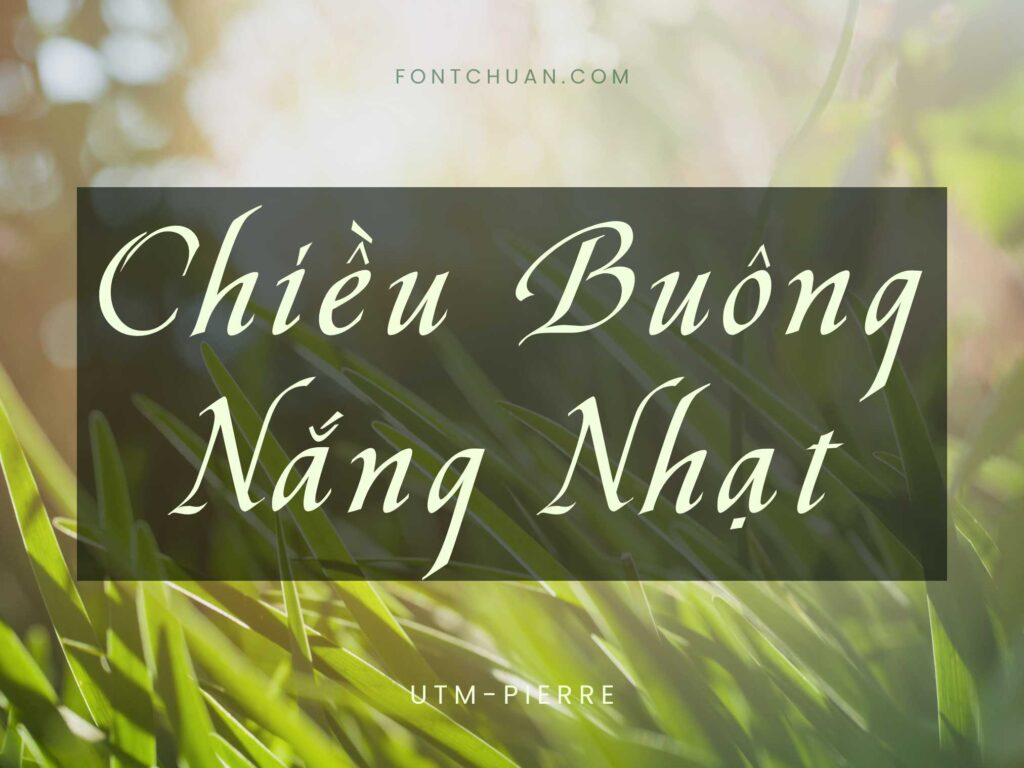
Font UTM Pierre Việt Hóa
UTM Pierre là một font chữ serif mang phong cách cổ điển và sang trọng, được thiết kế để tạo nên sự tinh tế và chuyên nghiệp trong các dự án thiết kế đồ họa. Font này có các đường nét thanh mảnh, độ tương phản cao và chân chữ rõ ràng, giúp tăng cường khả năng đọc và thu hút sự chú ý. Font đã được Việt hóa để hỗ trợ tiếng Việt, mở rộng khả năng ứng dụng trong nhiều lĩnh vực thiết kế. Thành viên của Font Chuẩn đã sưu tầm và giới thiệu font này nhằm đáp ứng nhu cầu bạn đọc, cung cấp nguồn tham khảo chất lượng và ứng dụng thực tế vào các dự án thiết kế
Với thiết kế cổ điển và thanh lịch, UTM Pierre phù hợp cho nhiều ứng dụng như thiết kế logo, tiêu đề, bao bì sản phẩm, ấn phẩm in ấn và nội dung thương hiệu. Các ngành nghề như quảng cáo, giáo dục, thiệp cưới và công nghệ có thể tận dụng font này để tạo nên sự sang trọng và chuyên nghiệp trong các sản phẩm thiết kế